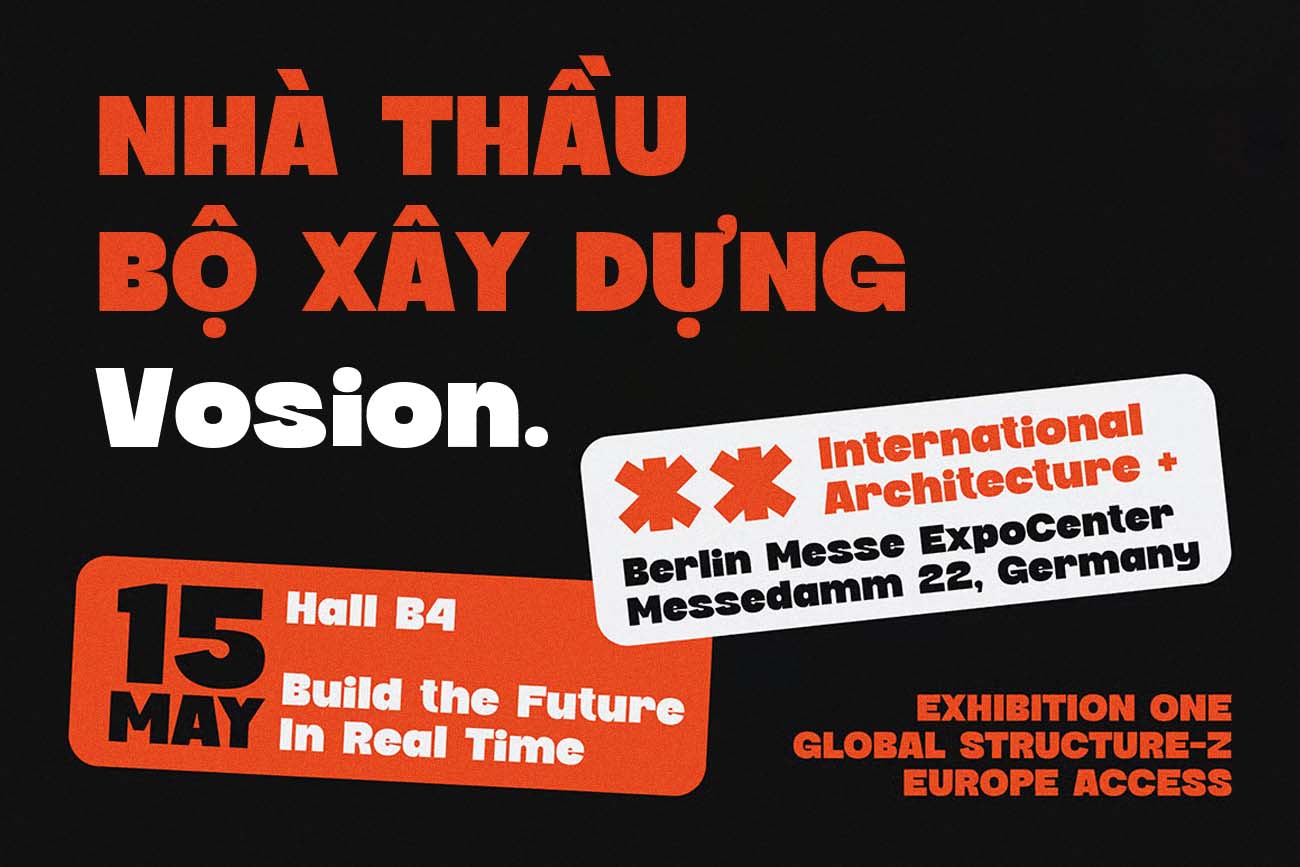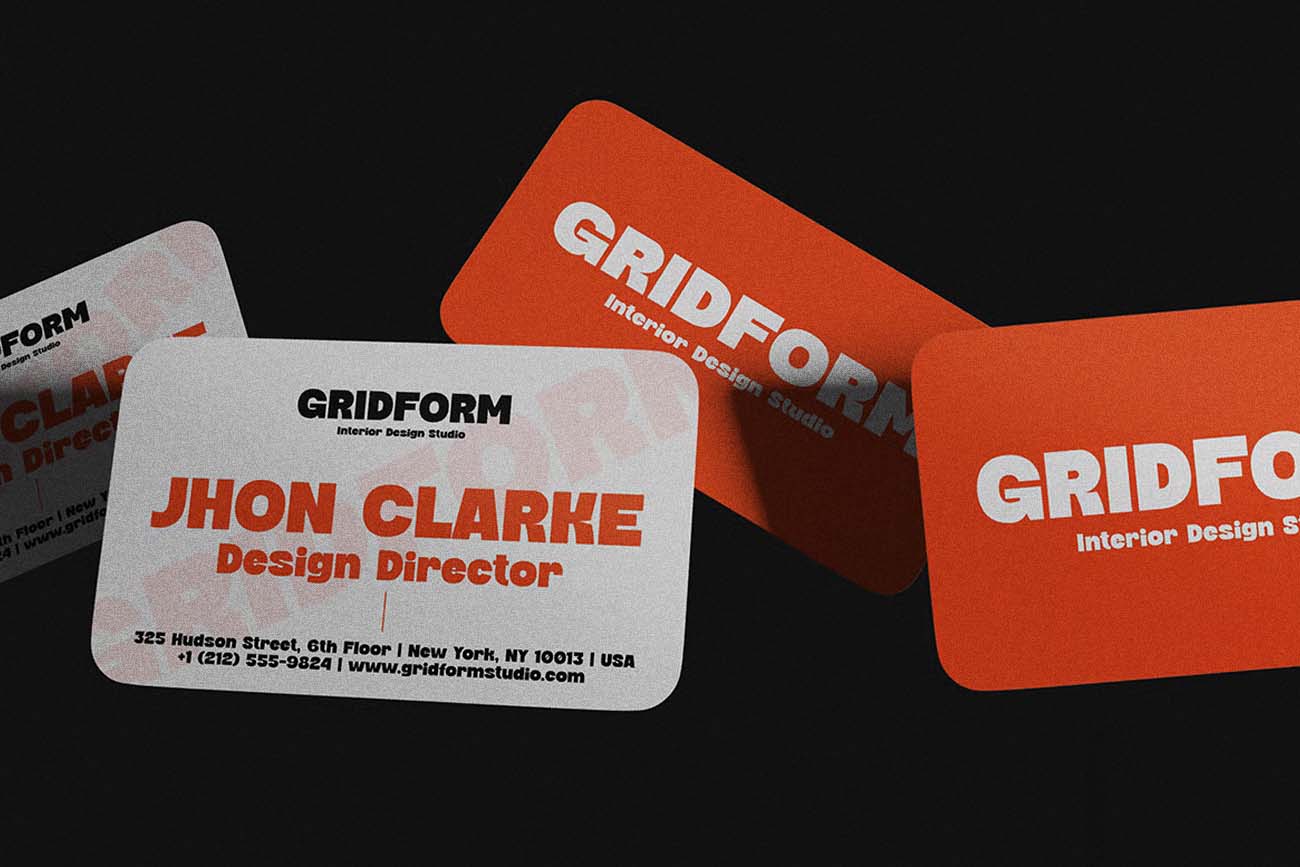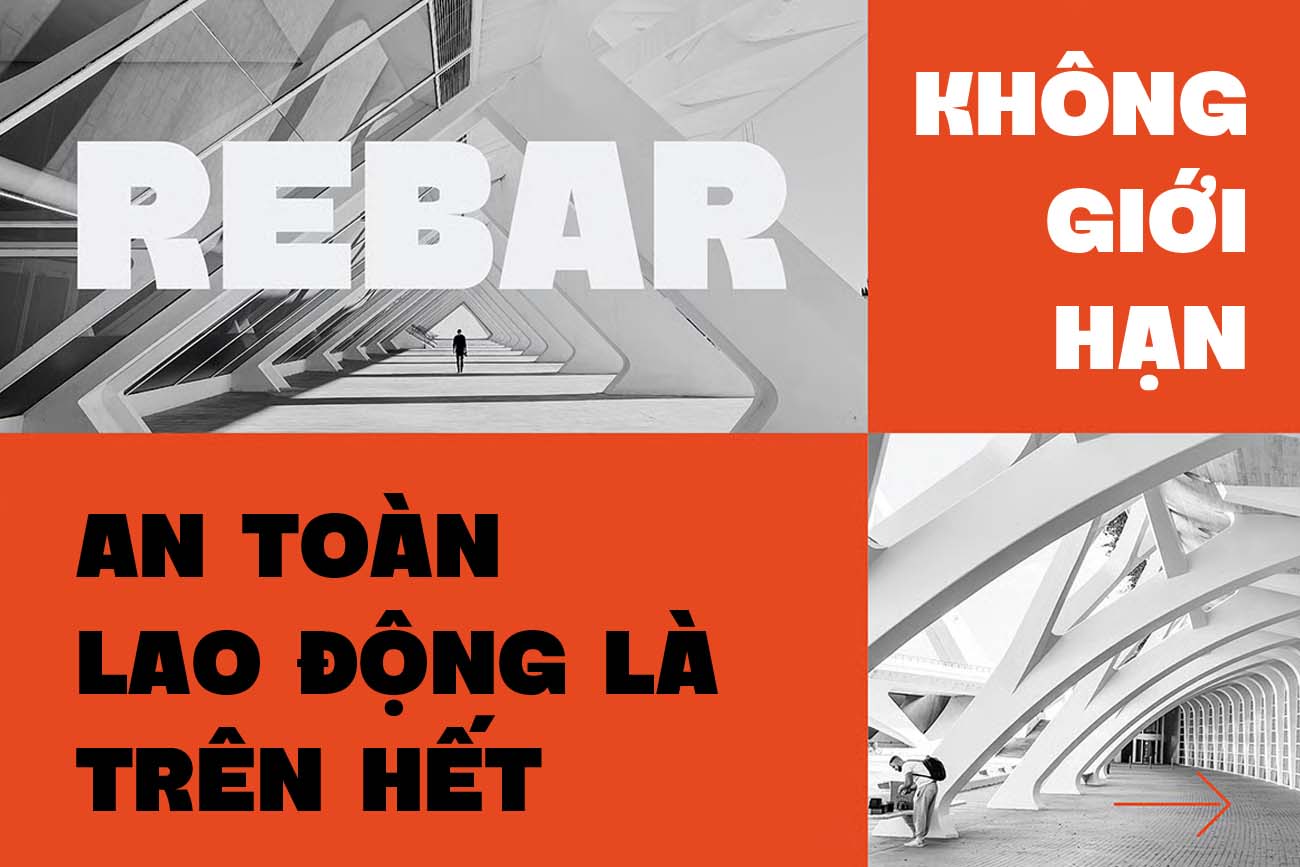
Phông chữ cứng cáp cho ngành xây dựng - TH Rebar Việt hóa
Giới thiệu
TH Rebar là một kiểu chữ sans serif đậm nét, mang phong cách công nghiệp, được Việt hóa hoàn chỉnh để phục vụ các dự án thiết kế trong ngành xây dựng, kiến trúc và thương hiệu kỹ thuật. Với kết cấu gọn gàng, các đường nét dày dặn và khối chữ vuông vức, TH Rebar đem lại cảm giác rắn rỏi, quyết đoán và dễ gây ấn tượng ngay từ cái nhìn đầu tiên.
Đặc điểm nổi bật
Phông chữ này gây ấn tượng bởi các đường nét dày, vuông vức và rõ ràng, gợi liên tưởng đến thép, bê tông và các khối kết cấu công nghiệp. Kiểu dáng sans serif hiện đại kết hợp với tỷ lệ cân đối, khoảng cách chữ hợp lý giúp văn bản luôn dễ đọc, ngay cả khi sử dụng ở kích thước lớn.
Ứng dụng trong thiết kế
TH Rebar đặc biệt phù hợp với các ngành nghề cần nhấn mạnh sự bền vững và chuyên nghiệp. Font có thể dùng trong thiết kế logo công ty xây dựng, bất động sản, poster triển lãm kiến trúc, banner quảng bá công trình hay các ấn phẩm thương hiệu doanh nghiệp. Ngoài ra, nó cũng thích hợp cho các mẫu namecard, bao bì và ấn phẩm marketing cần sự vững chãi.